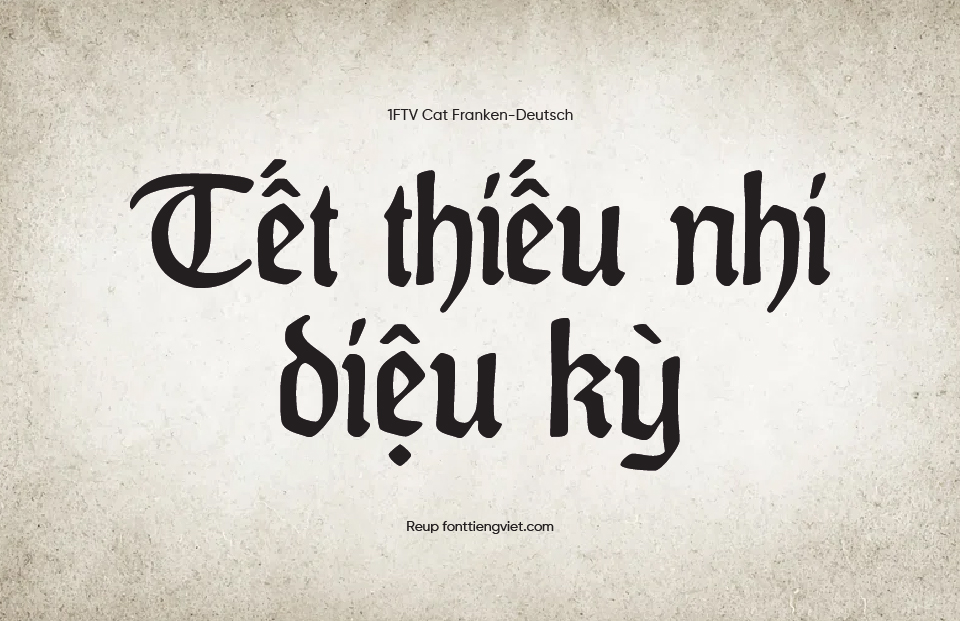
Mùa Trung Thu thường gắn liền với những đường nét mềm mại, uyển chuyển của font chữ thư pháp hoặc sự mộc mạc của font chữ cổ điển. Tuy nhiên, nếu bạn đang tìm kiếm một sự đột phá thị giác, một điểm nhấn cá tính và mạnh mẽ để làm mới các thiết kế lễ hội năm nay, thì Font Việt hóa 1FTV Cat Franken Deutsch chính là một ứng cử viên vô cùng sáng giá trong bộ sưu tập font trung thu của bạn.
Đặc Điểm Nổi Bật Của 1FTV Cat Franken Deutsch
Vốn mang hơi hướng Gothic (Blackletter) phá cách đan xen với nét hiện đại, 1FTV Cat Franken Deutsch mang đến một vẻ đẹp huyền bí, ma mị nhưng lại cực kỳ cuốn hút. Khi được ứng dụng khéo léo, phông chữ này mang lại một góc nhìn hoàn toàn mới cho các ấn phẩm Á Đông.
• Đường nét góc cạnh, đậm chất nghệ thuật: Các nét chữ dày, vuông vức kết hợp với những đường vát sắc sảo tạo nên một tổng thể vô cùng vững chãi và nổi bật.
• Dấu tiếng Việt hoàn thiện: Mặc dù sở hữu form chữ phức tạp, bộ font đã được việt hóa chỉn chu. Các dấu câu được thiết kế đồng bộ với thân chữ, đảm bảo khả năng hiển thị tiếng Việt mượt mà, không bị xô lệch khoảng cách (kerning).
• Sức hút từ sự bí ẩn: Phông chữ gợi lên cảm giác về những câu chuyện thần thoại, cổ tích xa xưa, rất thích hợp để kể những “Sự tích đêm rằm” theo một phong cách hiện đại và ma mị hơn.
Ứng Dụng Bất Ngờ Làm Font Trung Thu
Chính sự khác biệt của font việt hóa 1FTV Cat Franken Deutsch lại mở ra những cơ hội sáng tạo không giới hạn cho các designer trong dịp lễ này:
• Thiết kế hộp bánh Trung Thu phá cách: Phù hợp cho các dòng sản phẩm bánh Trung Thu cao cấp hướng tới giới trẻ, hoặc các phiên bản giới hạn (Limited Edition) có concept độc lạ, huyền bí.
• Poster sự kiện đêm rằm: Cực kỳ bắt mắt khi dùng làm Typography chính cho các sự kiện phá cỗ, rước đèn kết hợp với âm nhạc điện tử, lễ hội lồng đèn quy mô lớn mang màu sắc hiện đại.
• Ấn phẩm truyền thông nghệ thuật: Tạo điểm nhấn mạnh mẽ cho các bài đăng mạng xã hội, kết hợp tuyệt vời với các gam màu tương phản cao như Đen – Vàng Gold, Đỏ thẫm – Bạc.
Mẹo Thiết Kế (Typography Tips)
Do 1FTV Cat Franken Deutsch là một phông chữ có độ “nặng” và tính trang trí rất cao, bạn chỉ nên sử dụng nó cho các tiêu đề ngắn (Heading/Title). Để bản thiết kế đạt độ hài hòa tốt nhất, hãy kết hợp nó với các font chữ Sans-serif (không chân) cơ bản, rõ ràng cho phần nội dung chi tiết. Việc thêm hiệu ứng chữ nổi (Bevel/Emboss) hay đổ bóng (Drop Shadow) sẽ làm tăng thêm chiều sâu và sự hoành tráng cho dòng chữ.
Tổng Kết
Vượt ra khỏi những khuôn khổ thông thường, Font Việt hóa 1FTV Cat Franken Deutsch là minh chứng cho việc sáng tạo không có giới hạn. Hãy bổ sung ngay phông chữ độc đáo này để tạo ra những tác phẩm thiết kế Trung Thu mang đậm dấu ấn cá nhân và khiến người xem không thể rời mắt.